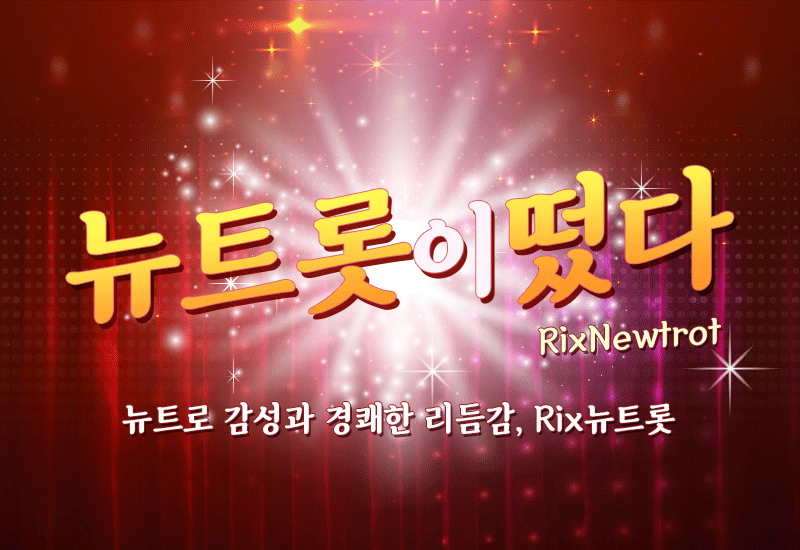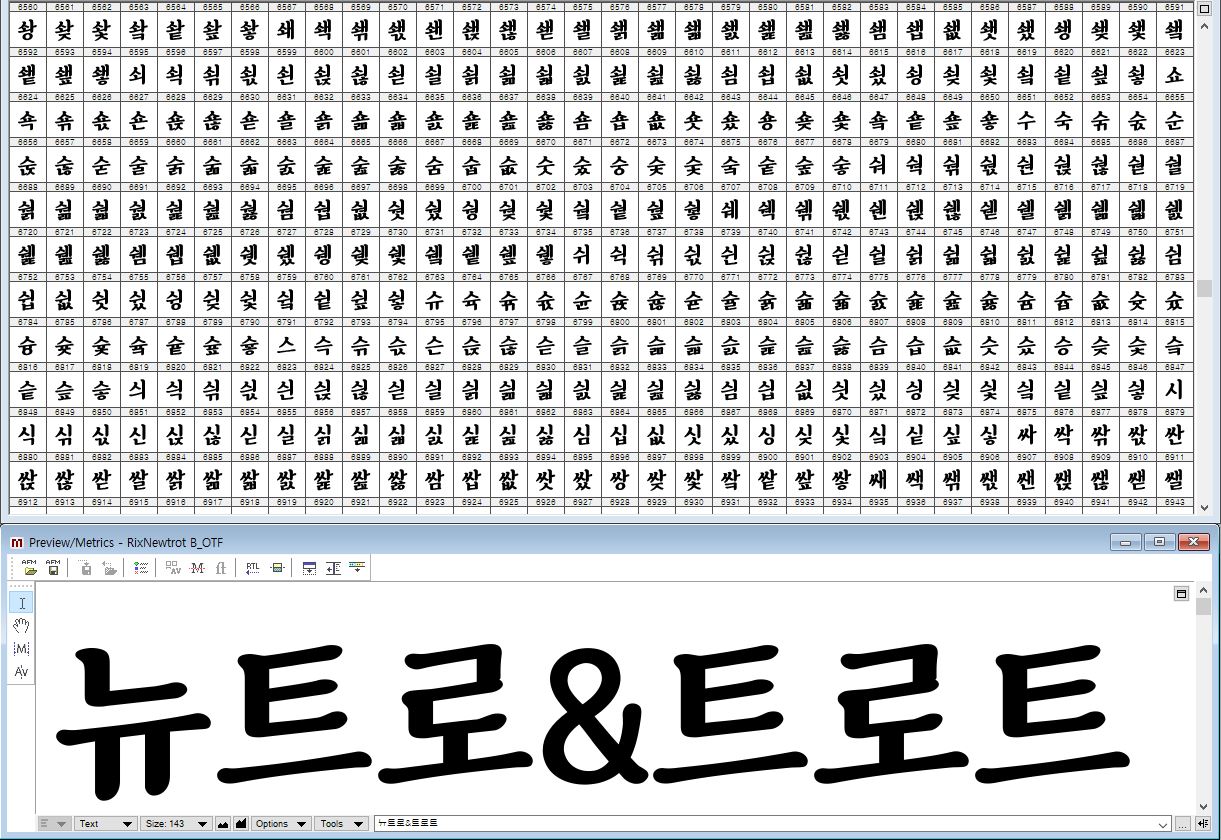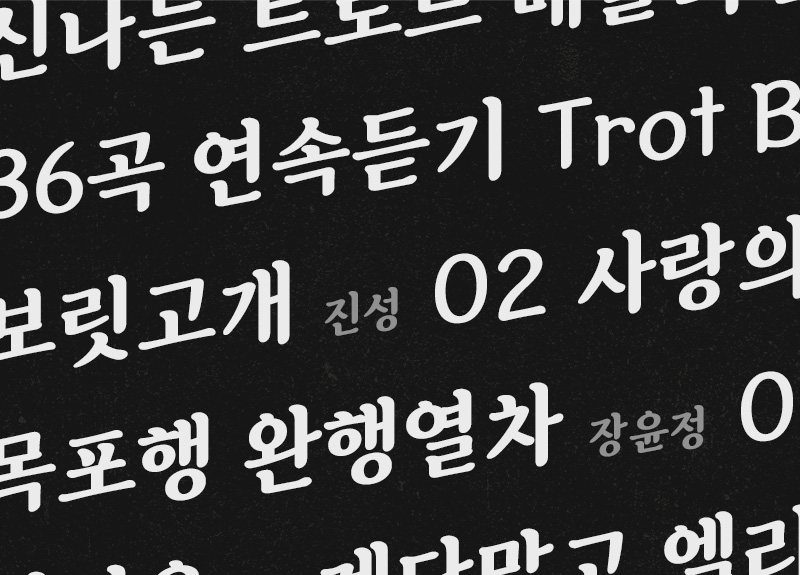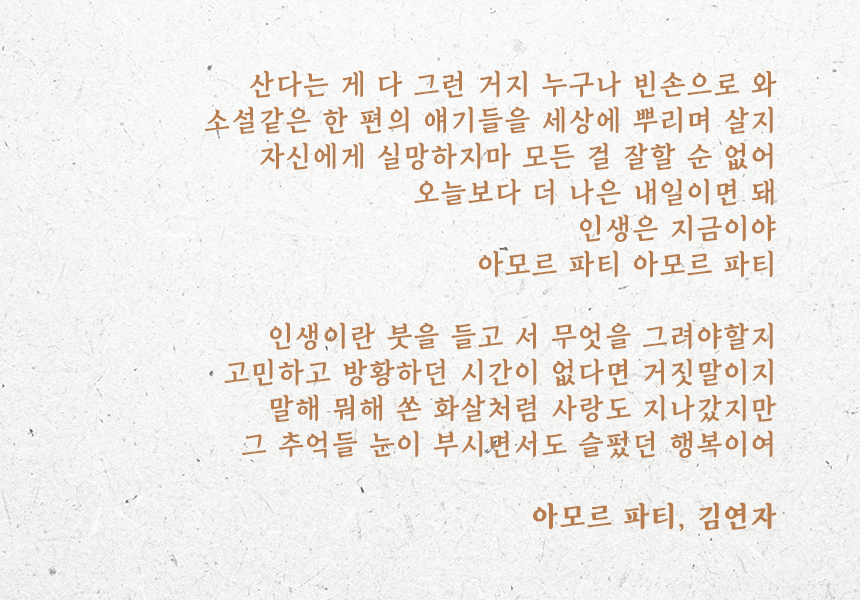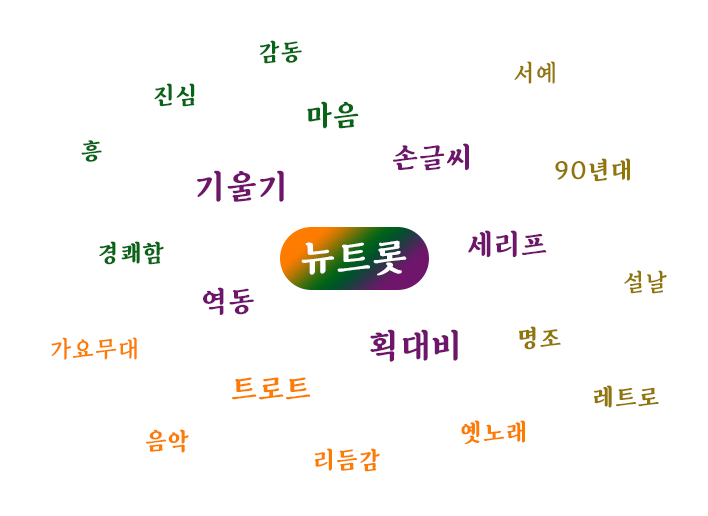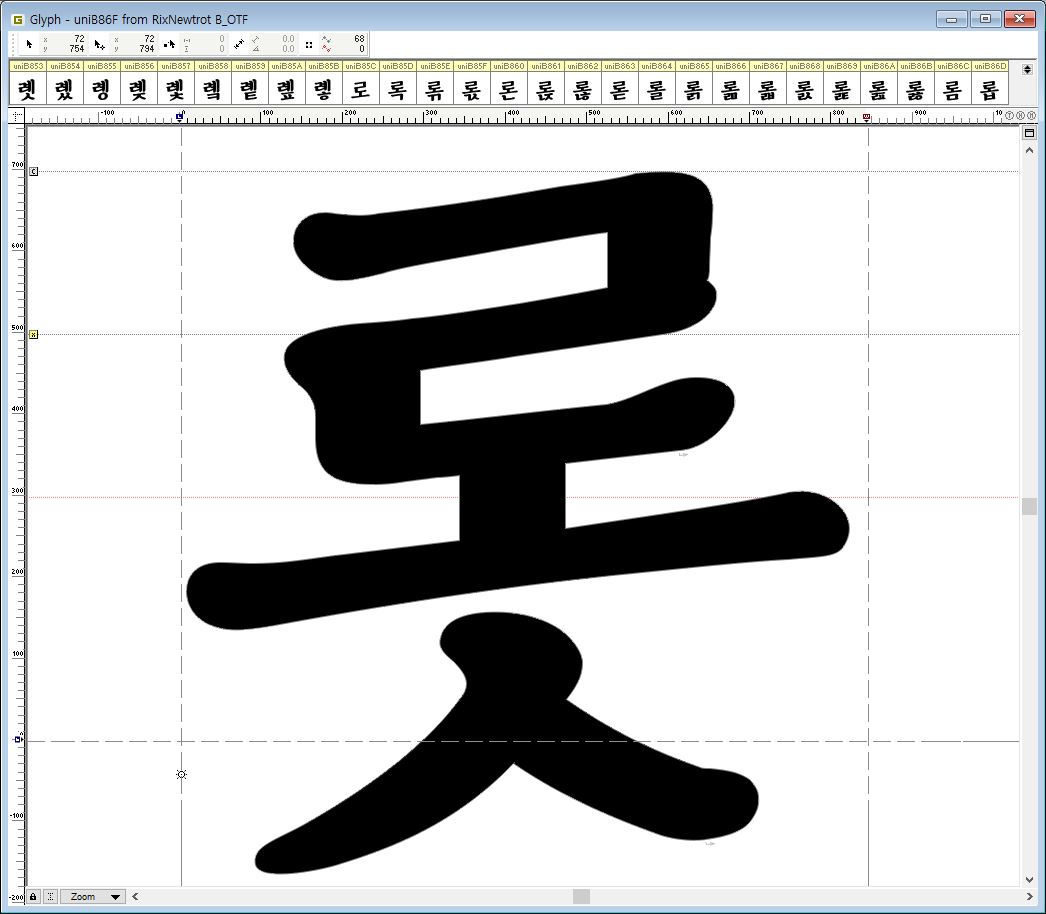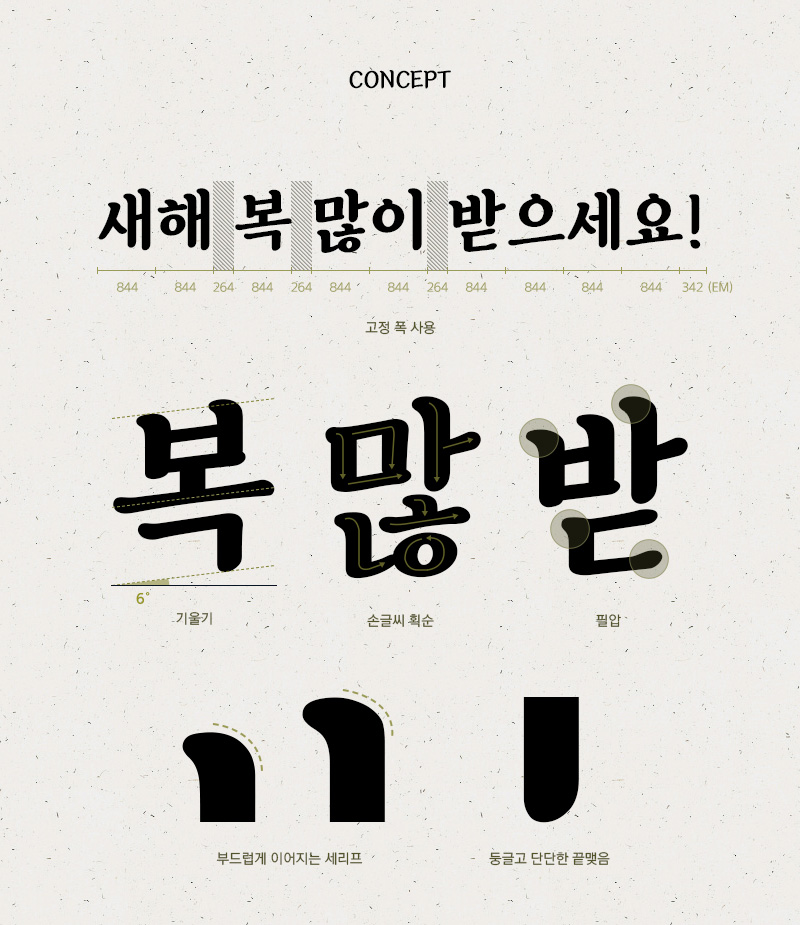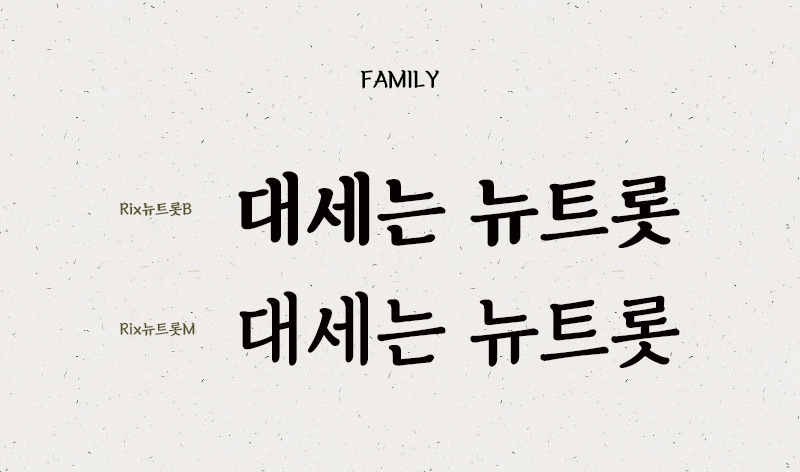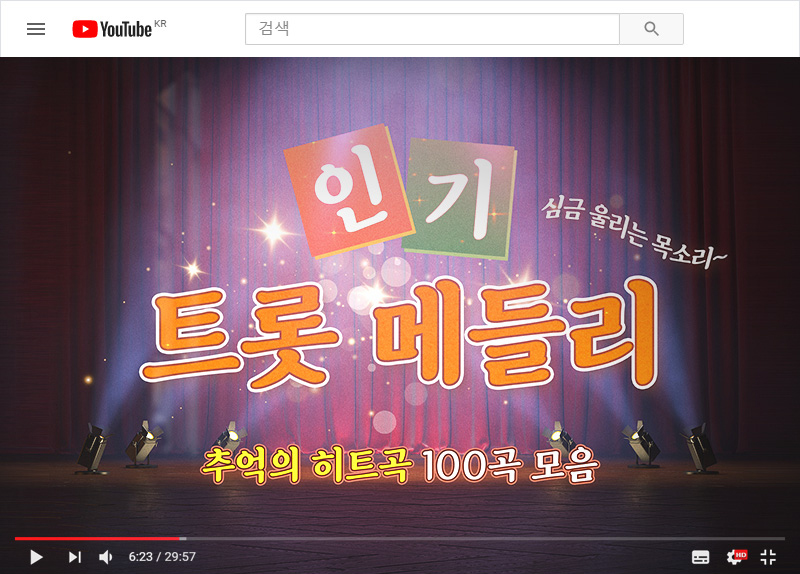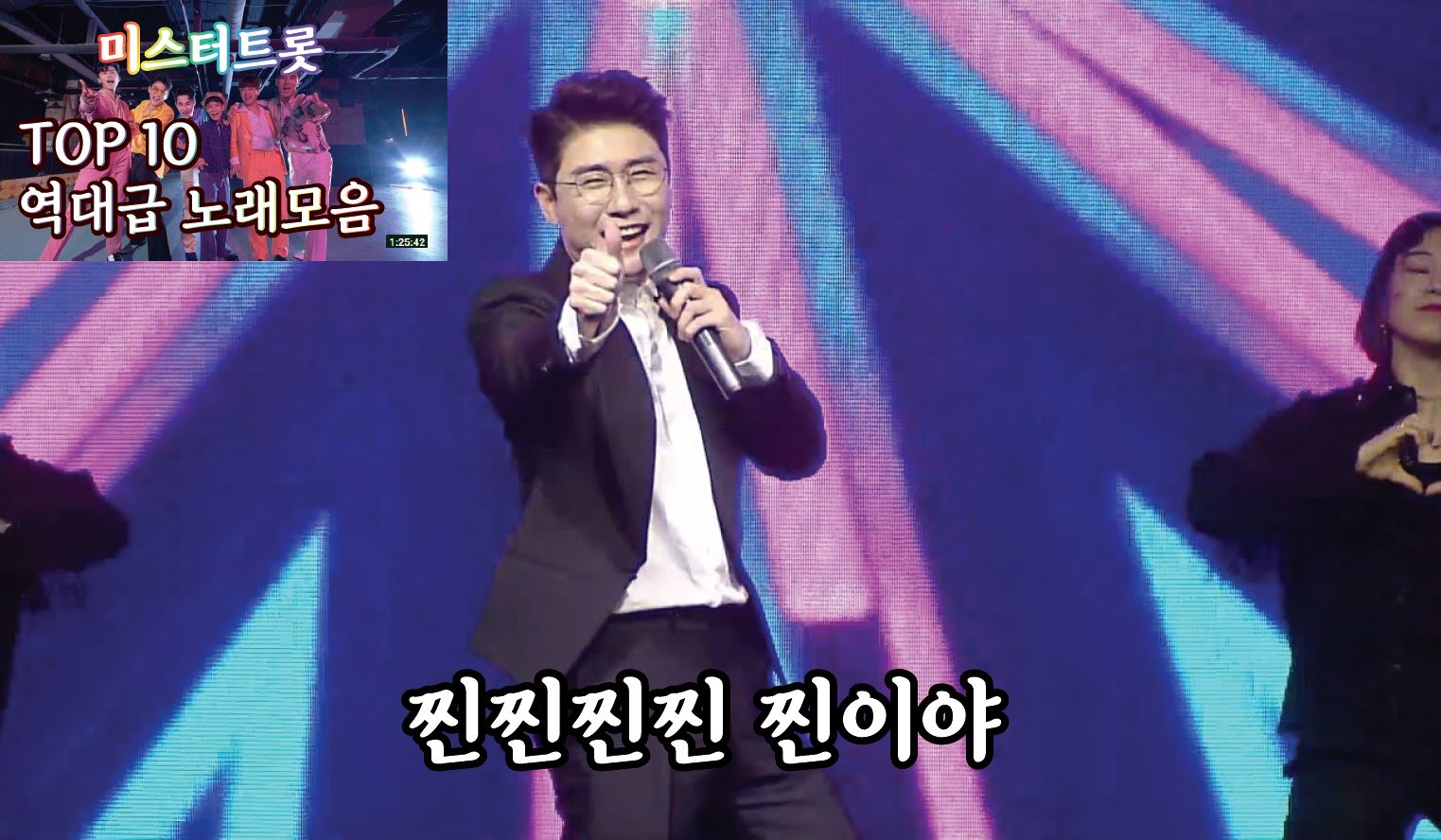
2021년 새해와 함께 출시하게 된 신축년 새로운 폰트를 소개합니다. 이름만 들어도 뭔가 느낌이 오는데요~ 바로「Rix뉴트롯」이 그 주인공입니다. TV 어딜 틀어도 트로트가 나오는 요즘, 릭스폰트도 그에 발맞춰 트로트와 꼭 어울리는 폰트를 출시했습니다. 벌써 어떤 폰트일지 너무너무 기대가 되는데요. 제작자인 박윤상 디자이너와의 인터뷰 먼저 보고 가실게요:)
2021년 새해에 맞춰 출시된 이번 폰트, Rix뉴트롯에 대해 살짝 소개 부탁드려요!
붓으로 눌러쓴듯한 명조형 손글씨 폰트입니다. 기울기가 있게 제작되어 손으로 쓴듯한 느낌이 더 나는 것 같아요. 가로, 세로에 획 대비와 강약 조절로 리듬감이 느껴지는데 간드러지는 트로트와 비슷한 것 같아요. 또한 두 가지 굵기로 제작되어 사용할 수 있는 범위를 넓혔습니다.
2020년은 트로트로 시작해 트로트로 마감한 해라고 해도 과언이 아닐 텐데요. 역시 뉴트롯은 트로트를 겨냥해 제작한 서체라고 봐도 될까요?
평소에 자사 서체를 제작할 때에는 타깃과 시장성보다는 재밌고 특이하고 폰트 시장에서 보기 드문 시안을 많이 만드는 편인데 이번에는 시장성과 요즘 트렌드를 알아보려고 했어요. 폰트가 많이 사용되는 TV 프로그램들에서 시청률이 높은 대부분의 프로그램이 트로트 관련 방송들이었어요. 그래서 트로트 프로그램 자막들에서 많이 사용될 수 있도록 포커싱 해서 제작된 서체입니다. 마침 오픈도 1월에 하다 보니 신년 맞이와도 어울리는 것 같아 좋은 것 같아요!
Rix뉴트롯 폰트의 디자인에 있어서 가장 신경 쓴 부분은 무엇인지?
아무래도 기울기가 들어간 서체다 보니 글줄이 흔들릴까 가 제일 걱정이 많이 되었답니다. 위치를 잘 맞춘 것 같다가도 다른 글자랑 붙여보면 살짝 올라가 보이기도 하면서 내려가 보이기도 하고, 그 부분을 조율하는 게 가장 어려웠고, 세리프 있는 서체를 처음 제작하다 보니 세리프의 시작과 끝의 느낌을 맞춰주는 부분도 처음 시안 단계에서 고민이 많았답니다.
Welcome to 뉴-트롯 World
그 이유는 휴먼 터치Human Touch가 필요한 요즘 시기 때문이 아닐까 싶습니다. 많은 것이 단절되고 만남이 어려워진 언택트untact, 그리고 온택트ontact 시대. 다르게 말하자면 사람의 온기를 느끼기 힘든 시대입니다. 트로트는 이런 시기에 차가워진 사람들의 마음을 녹이고, 공감과 감동을 불러일으켰습니다. 그런 트로트처럼 마음을 꾹꾹 눌러 담은 듯한 손글씨, 힘이 있지만 온기가 느껴지는 옛 필체의 느낌을 담아 폰트를 제작했습니다.
뉴트로 감성 한 스푼.
Rix뉴트롯은 뉴트로New+Retro 감성과 경쾌한 트로트를 모티브로 제작한 명조형 손글씨 서체입니다. 꾸준히 인기 있는 뉴트로, 레트로 감성. 옛 느낌이 나는 명조체가 기본 베이스지만 적절한 획 대비와 강약 조절 그리고 기울기를 주어 경쾌한 리듬감이 느껴지게 했죠. 어떻게 제작했는지 한 번 자세히 살펴볼까요?
뉴트로 감성과 리듬감이 느껴지면서도 단단하고 안정적인 서체를 만들기 위해 많은 연구가 필요했습니다. 박윤상 디자이너가 인터뷰에서 말했듯 기울기 있는 서체의 글줄을 맞추는 것이 굉장히 어렵지만 여러 번의 수정을 통해 적정 비율을 맞추었습니다.
글자의 컨셉과 디자인
손글씨 획순을 따른 글자는 옛 명조체의 느낌이 많이 납니다. 강약 조절로 필압이 느껴지게 하고 기울기를 주어 실제로 손으로 쓴 것과 같은 느낌을 주었습니다. 또한 부드러운 세리프와 둥글고 단단한 끝맺음으로 세련미가 느껴지도록 했습니다.
폰트의 굵기는 Bold와 Medium 두 가지로 제작하여 제목이나 본문 모두 다양하게 사용할 수 있도록 했습니다.
| Rix뉴트롯 적용 이미지 샘플
뉴트롯 폰트는 아무래도 트로트 관련 방송 자막, 유튜브 썸네일, 노래 자막 등에 활용도가 높을 것으로 예상됩니다. 뉴트로와 트로트의 궁합이 좋은 만큼 Rix뉴트롯 서체도 아-주 찰떡쿵으로 어울립니다.
인쇄물, 패키지 등에도 다양한 활용을 기대할 수 있습니다. 신년 인사 카드나 엽서, 세련된 옛 느낌을 내고 싶은 패키지에 사용하면 자연스럽게 어우러집니다. 명조형 서체로 높은 가독성도 한몫하겠죠!